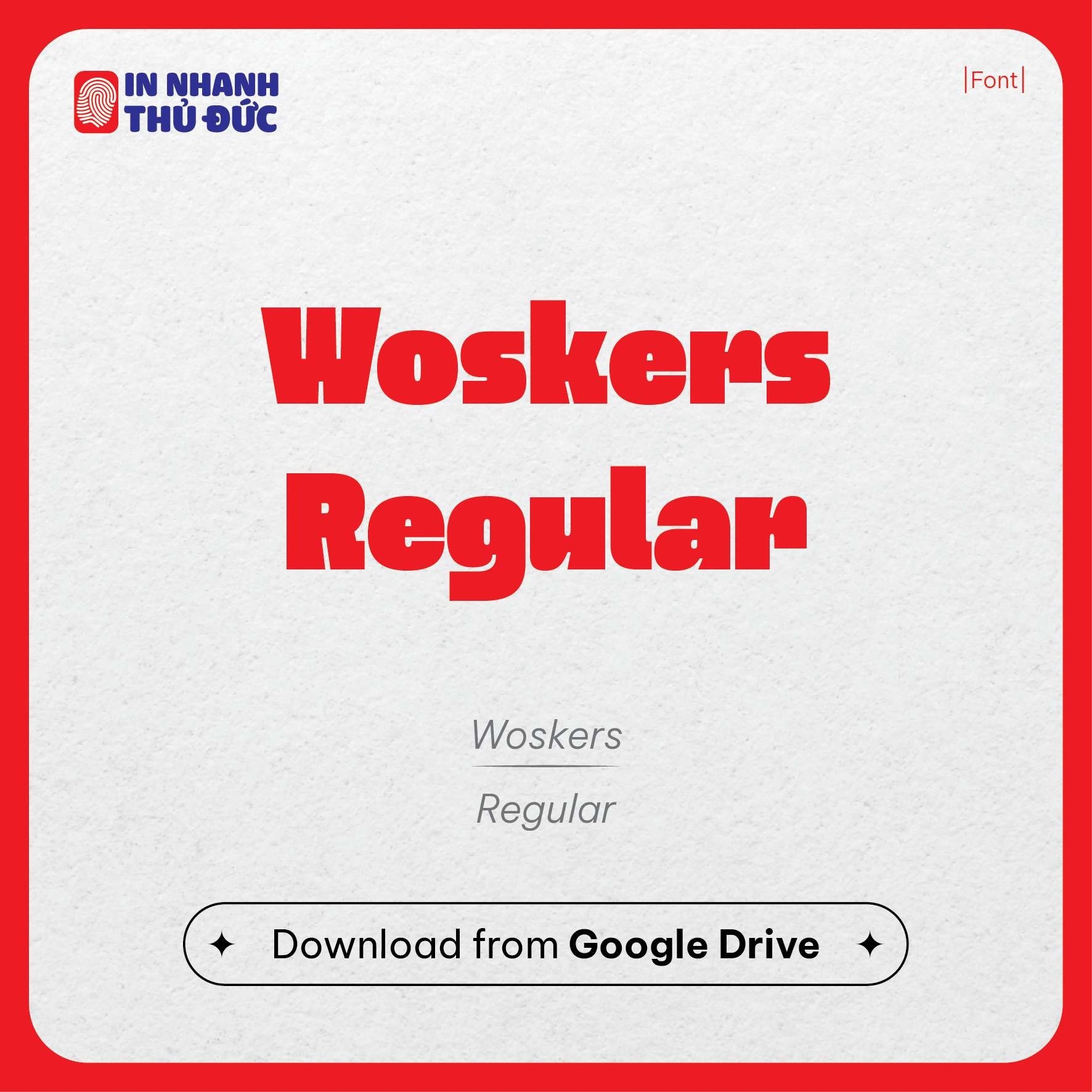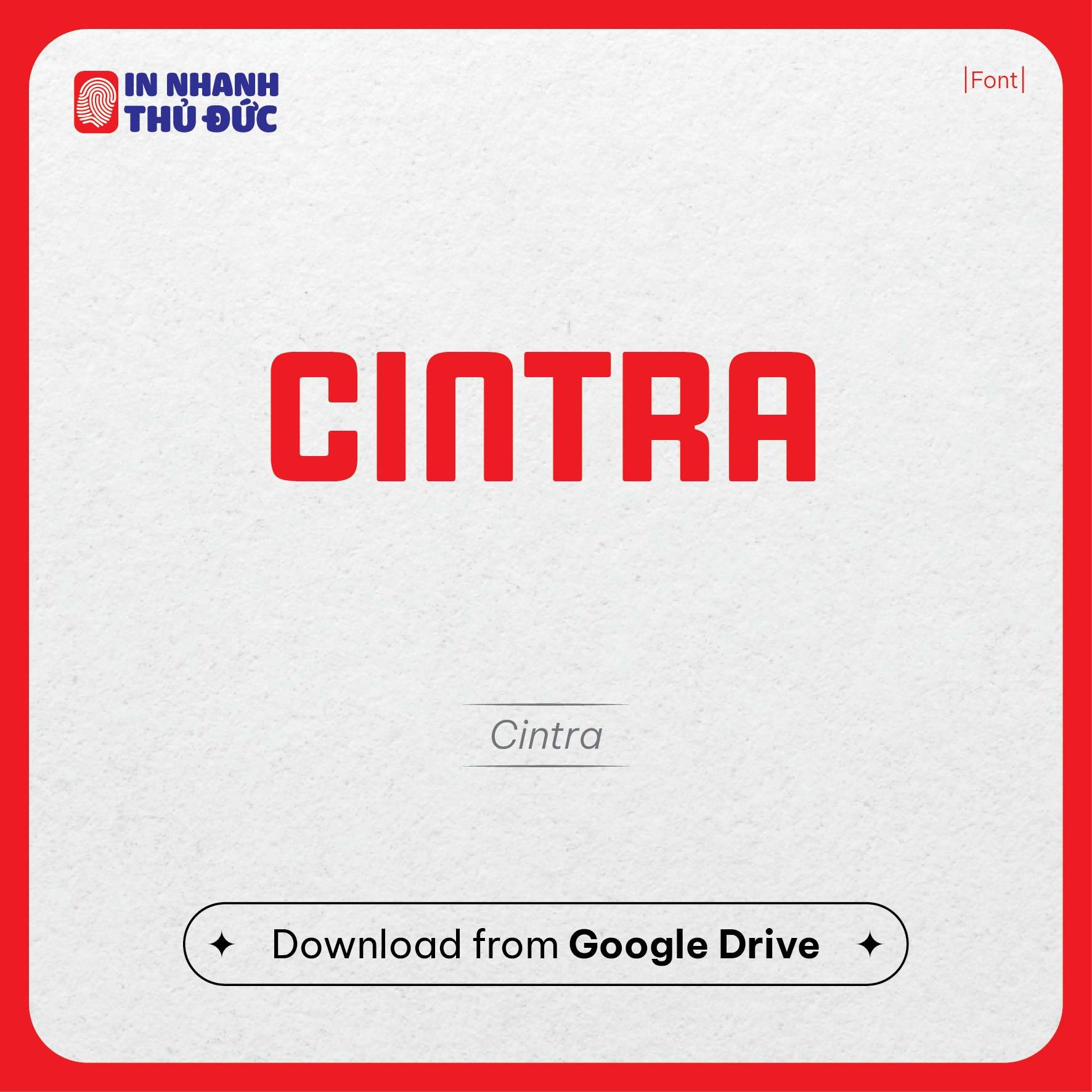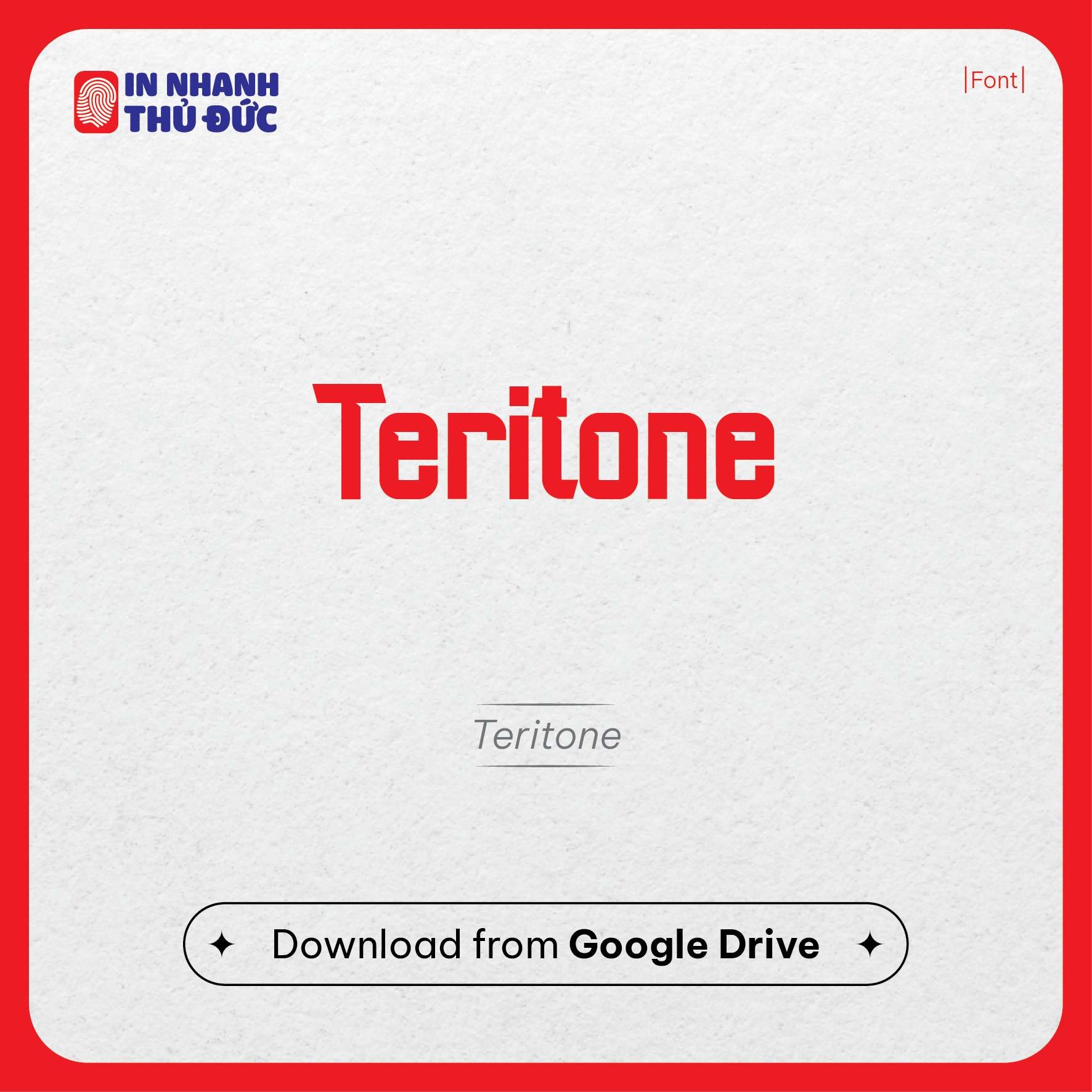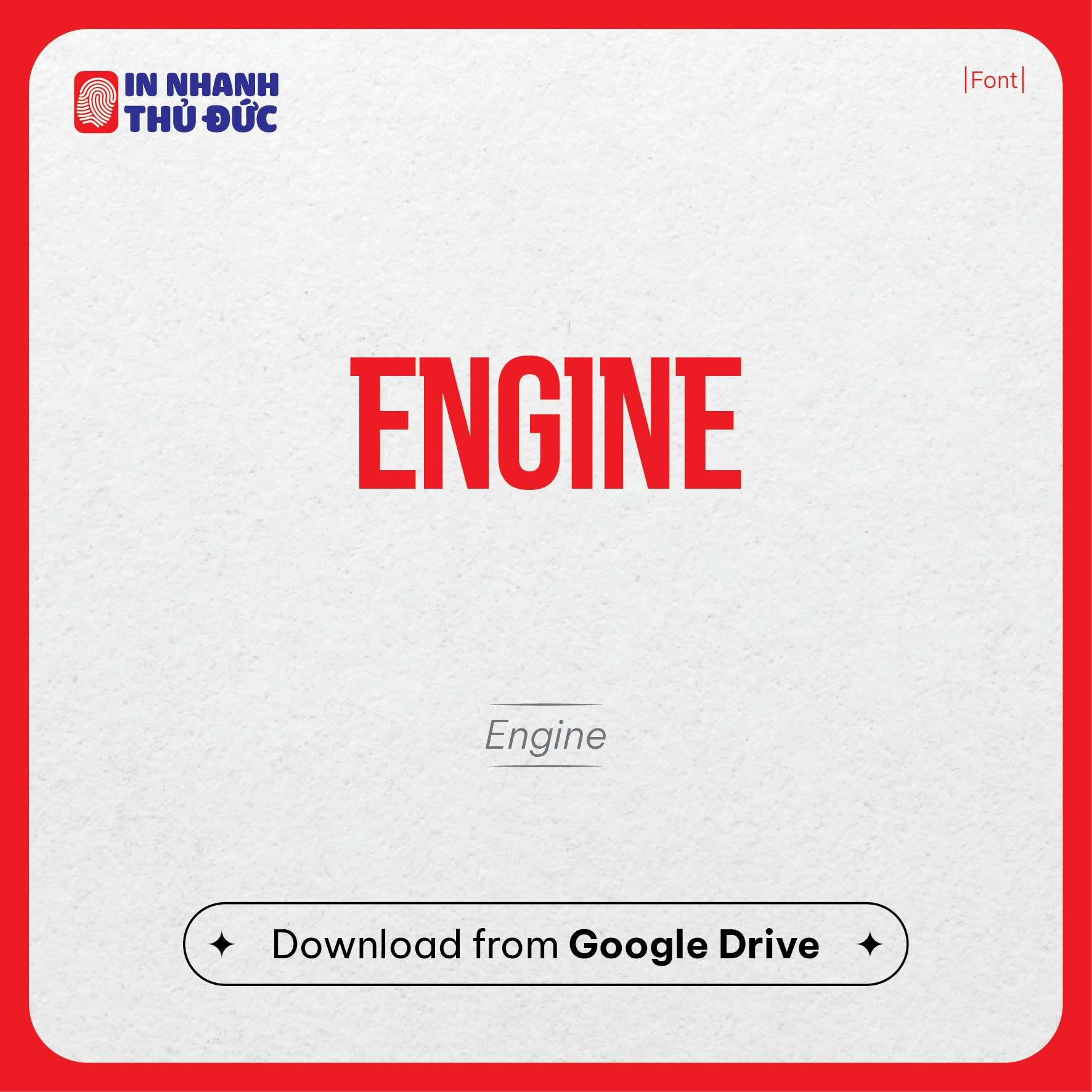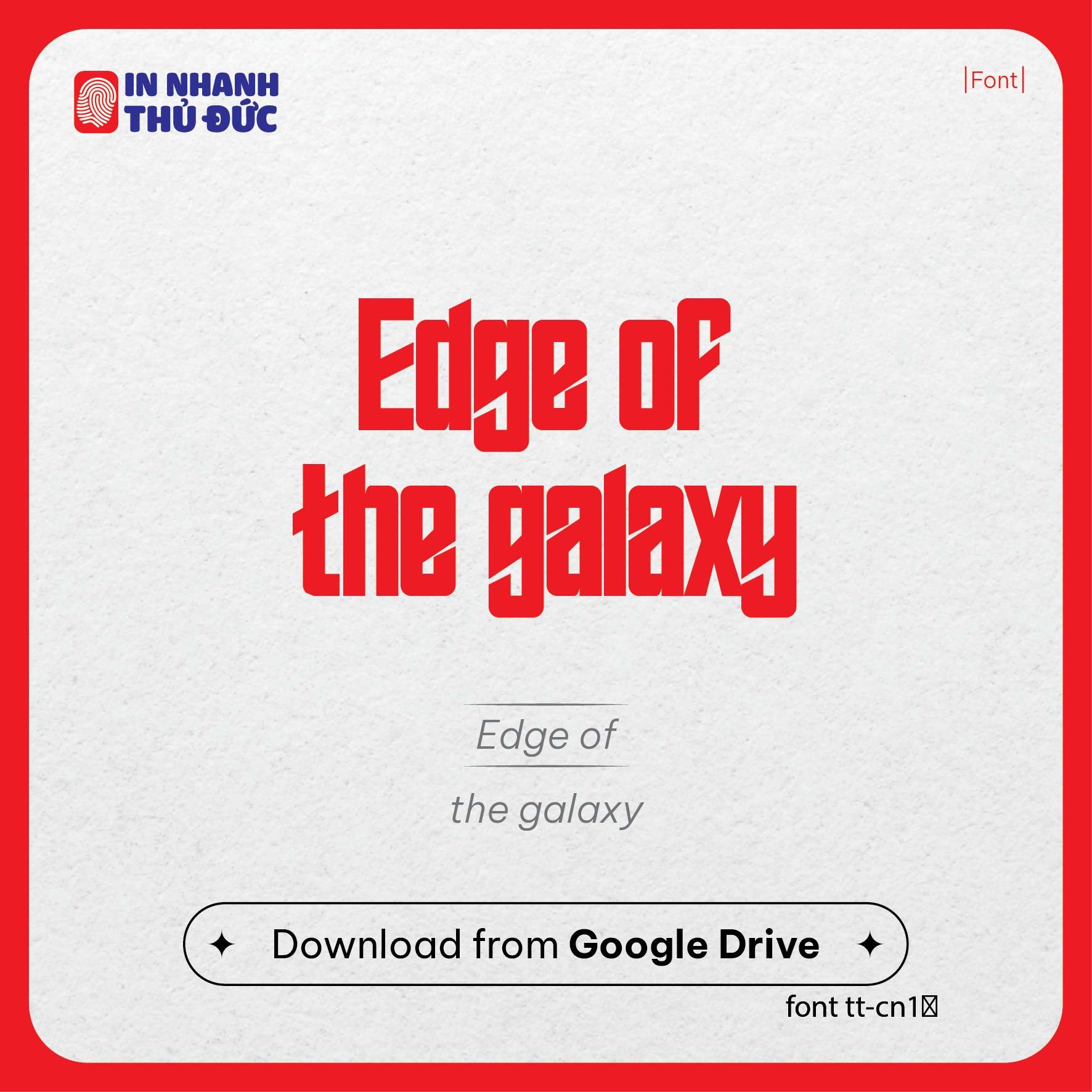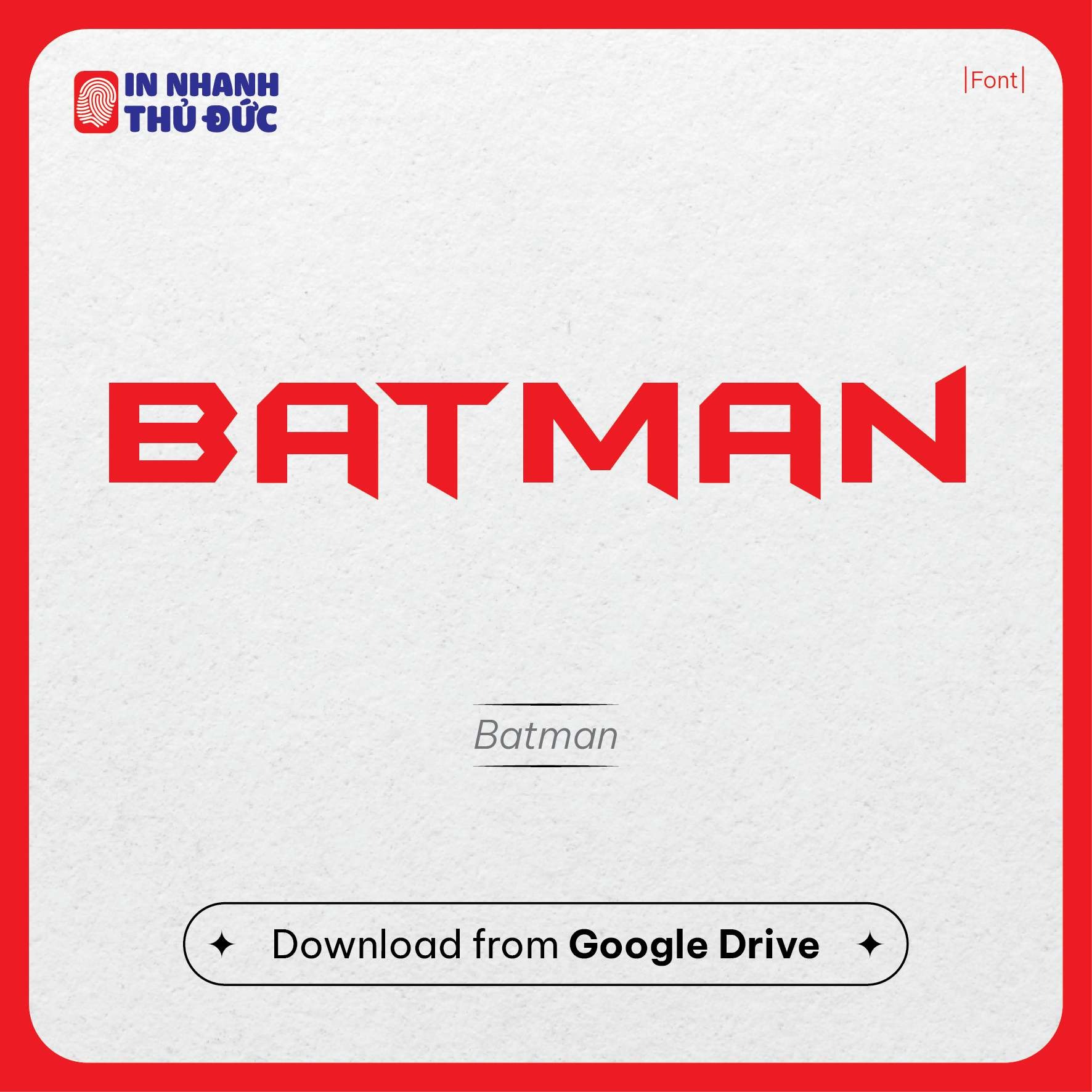
Bùng Nổ Thiết Kế Thể Thao: Top Font Chữ Đẹp & Miễn Phí
Trong thế giới thể thao, nơi cảm xúc, sức mạnh và tốc độ luôn ở mức cao nhất, từng chi tiết nhỏ trong thiết kế đều góp phần tạo nên ấn tượng và truyền tải tinh thần của đội bóng hay sự kiện. Và một trong những yếu tố "thầm lặng" nhưng có sức ảnh hưởng vô cùng lớn chính là font chữ. Một font chữ thể thao phù hợp không chỉ giúp thông điệp rõ ràng mà còn thổi bùng ngọn lửa cuồng nhiệt, khẳng định cá tính và tạo dấu ấn khó phai.
Hôm nay, In Nhanh Thủ Đức sẽ cùng bạn khám phá những font chữ thể thao đẹp, ấn tượng, và đặc biệt là có nhiều lựa chọn miễn phí, giúp bạn nâng tầm thiết kế của mình. Từ những cái tên mạnh mẽ như ENGINE, Batman, Cintra đến những font chữ cá tính như Woskers Regular, Edge of the Galaxy, hay Teritone được giới thiệu, chúng ta sẽ cùng phân tích và tìm ra lựa chọn hoàn hảo nhất!
Phần 1: Tại Sao Font Chữ Lại Quan Trọng Trong Thiết Kế Thể Thao?
Trước khi đi sâu vào các gợi ý cụ thể, hãy cùng tìm hiểu lý do vì sao font chữ lại đóng vai trò then chốt:
- Truyền Tải Năng Lượng & Cảm Xúc: Font chữ có khả năng khơi gợi cảm xúc. Một font chữ góc cạnh, đậm nét có thể thể hiện sức mạnh, sự quyết đoán, trong khi font chữ có đường nét uyển chuyển hơn lại mang đến cảm giác tốc độ, linh hoạt.
- Xây Dựng Nhận Diện Thương Hiệu: Logo đội bóng, tên vận động viên trên áo đấu, banner quảng cáo giải đấu... tất cả đều cần một font chữ đặc trưng để tạo sự nhất quán và dễ nhận diện.
- Tăng Tính Dễ Đọc: Đặc biệt trên áo đấu hoặc bảng tỷ số, font chữ cần rõ ràng, dễ đọc từ xa và ngay cả khi đối tượng đang chuyển động.
- Tạo Sự Chuyên Nghiệp: Một thiết kế sử dụng font chữ được lựa chọn kỹ lưỡng sẽ trông chuyên nghiệp và đáng tin cậy hơn hẳn.
Phần 2: Đặc Điểm Nhận Diện Một Font Chữ Thể Thao "Chất"
Không phải font chữ nào cũng phù hợp với chủ đề thể thao. Dưới đây là những đặc điểm thường thấy ở các font chữ thể thao ấn tượng:
- Mạnh Mẽ & Táo Bạo: Thường là các font Sans Serif (không chân) hoặc Slab Serif (chân vuông, dày) với độ đậm cao (Bold, Black, Heavy).
- Góc Cạnh & Dứt Khoát: Nhiều font có các đường nét sắc sảo, góc cạnh, tạo cảm giác năng động, quyết liệt.
- Hiện Đại & Năng Động: Mang hơi hướng tương lai, công nghệ, đặc biệt phù hợp với các môn eSports hoặc các thiết kế trẻ trung.
- Dễ Đọc Từ Xa: Ngay cả với các font cách điệu, tính dễ đọc vẫn cần được ưu tiên.
- Đôi Khi Có Yếu Tố "Grunge" hoặc "Stencil": Tạo vẻ gai góc, bụi bặm, phù hợp với các môn thể thao đường phố hoặc đối kháng.
Phần 3: Khám Phá Bộ Sưu Tập Font Chữ Thể Thao Đáng Chú Ý
Dựa trên các mẫu bạn cung cấp và xu hướng thế giới, đây là một số gợi ý font chữ và phong cách bạn có thể tham khảo:
1. Nhóm Font Sans Serif Hiện Đại & Mạnh Mẽ
Đây là nhóm font phổ biến nhất trong thể thao nhờ sự rõ ràng, hiện đại và khả năng truyền tải sức mạnh.
- ENGINE: Như tên gọi, font chữ này gợi đến sự cơ khí, mạnh mẽ và bền bỉ. Các đường nét dày, vuông vức rất phù hợp cho logo đội đua, các môn thể thao liên quan đến máy móc, hoặc những thiết kế cần sự vững chãi.
- Cintra: Một font chữ Sans Serif với các góc được bo nhẹ nhưng vẫn giữ được sự cứng cáp. Cintra mang vẻ hiện đại, dễ đọc, thích hợp cho tên cầu thủ trên áo, tiêu đề sự kiện.
- Teritone: Tương tự Cintra, Teritone cung cấp sự cân bằng giữa nét hiện đại và sự mạnh mẽ. Font này có độ mở vừa phải, giúp dễ đọc ở nhiều kích thước.
- Woskers Regular: Font chữ này có vẻ ngoài thân thiện hơn một chút nhưng vẫn giữ được độ đậm cần thiết. Các ký tự có tỷ lệ cân đối, phù hợp cho cả tiêu đề và phần văn bản ngắn trong các ấn phẩm thể thao.
2. Nhóm Font Cách Điệu & Đậm Chất "Siêu Anh Hùng"
Những font chữ này thường có thiết kế độc đáo, mang tính biểu tượng cao, giúp thiết kế của bạn nổi bật ngay lập tức.
- Batman: Lấy cảm hứng từ logo Batman kinh điển, font chữ này mang đậm nét mạnh mẽ, bí ẩn và đầy quyền lực. Rất tuyệt vời cho các đội tuyển có biệt danh liên quan đến động vật mạnh mẽ hoặc các thiết kế cần sự ấn tượng "ngầu".
- Edge of the Galaxy: Với các nét cắt xéo táo bạo và không gian âm thông minh, font này gợi đến sự bứt phá, phiêu lưu và công nghệ. Hoàn hảo cho eSports, các môn thể thao mạo hiểm hoặc thiết kế mang hơi hướng tương lai.
3. Nhóm Font "College" Cổ Điển
Đây là dòng font mang tính biểu tượng trong thể thao học đường Mỹ, thường là các font Slab Serif hoặc Sans Serif có đường viền (outline) hoặc bóng (shadow). Chúng gợi lên tinh thần đồng đội, truyền thống và sự tự hào.
- Ví dụ tham khảo: Jersey M54, Freshman, College Block.
- Ứng dụng: Logo đội bóng trường học, áo thi đấu, các thiết kế mang phong cách retro.
4. Nhóm Font Stencil & Industrial
Mang vẻ ngoài bụi bặm, cứng cáp, font stencil (khuôn tô) và industrial (công nghiệp) rất hợp với các môn thể thao đối kháng, đường phố, hoặc các thương hiệu muốn thể hiện sự gai góc.
- Ví dụ tham khảo: Octin Stencil, Capture It, DDay Stencil.
- Ứng dụng: Thiết kế cho MMA, boxing, skateboarding, các sự kiện thể thao ngoài trời.